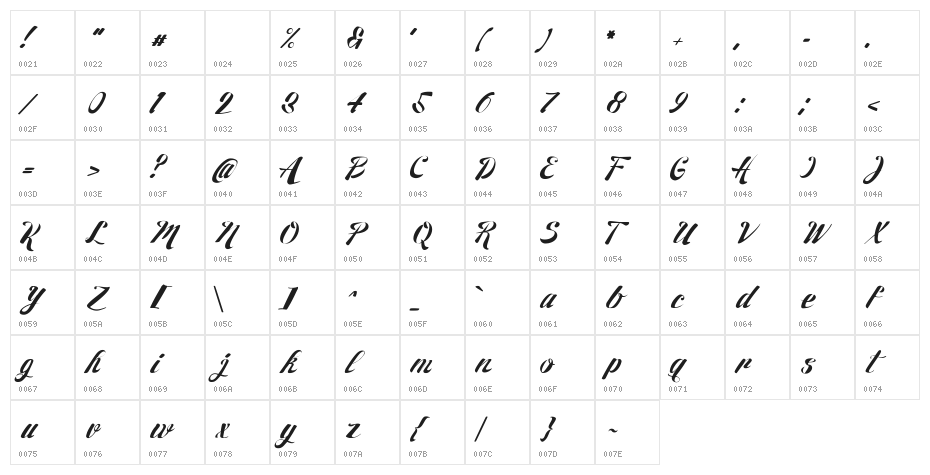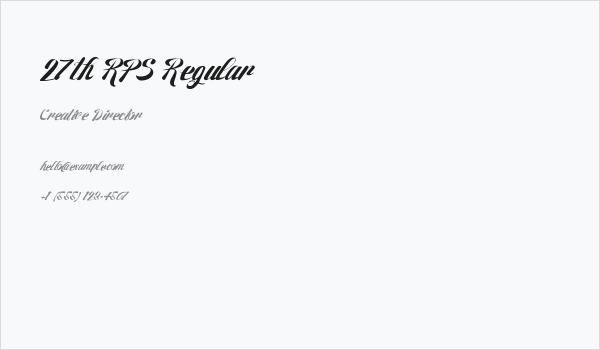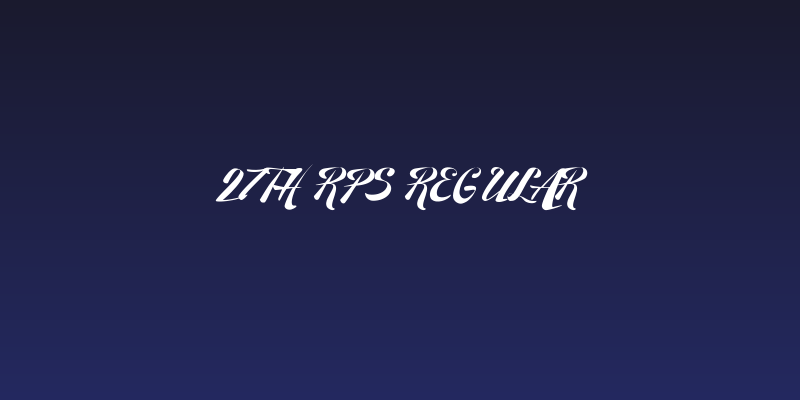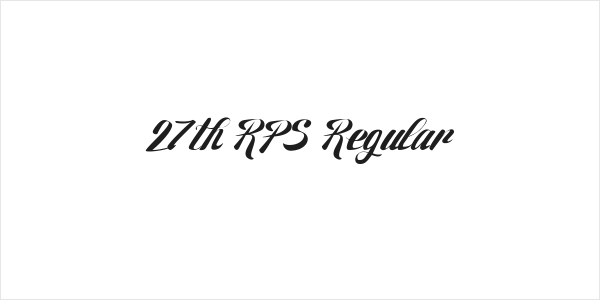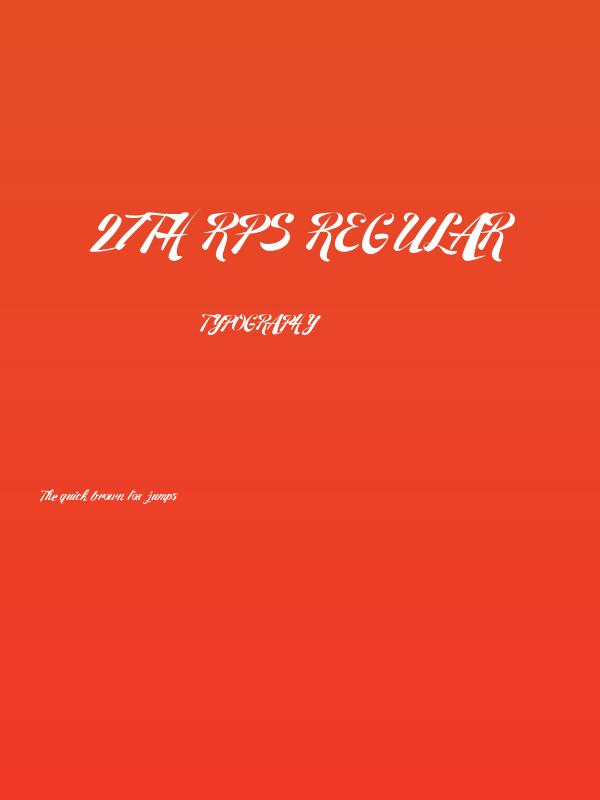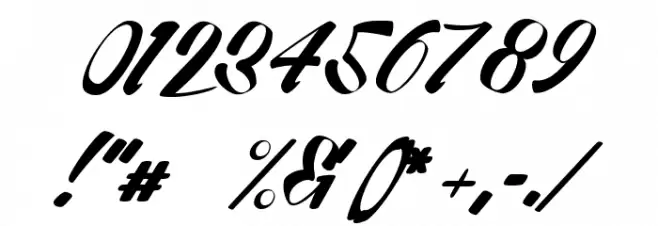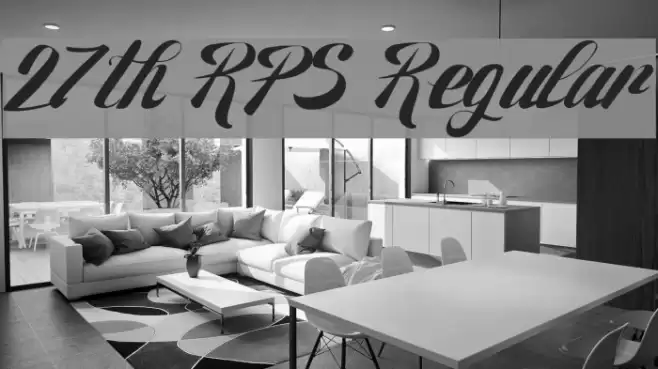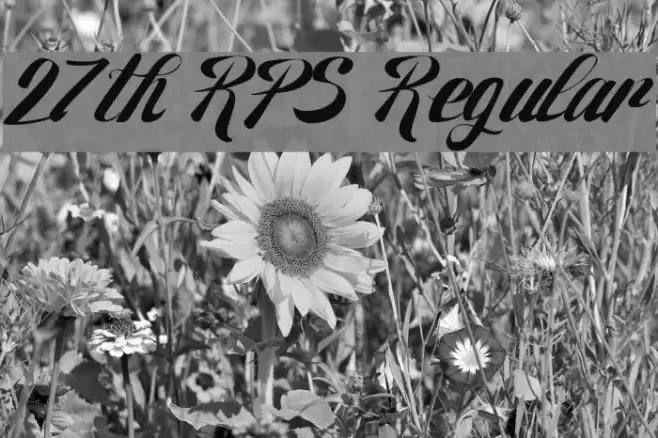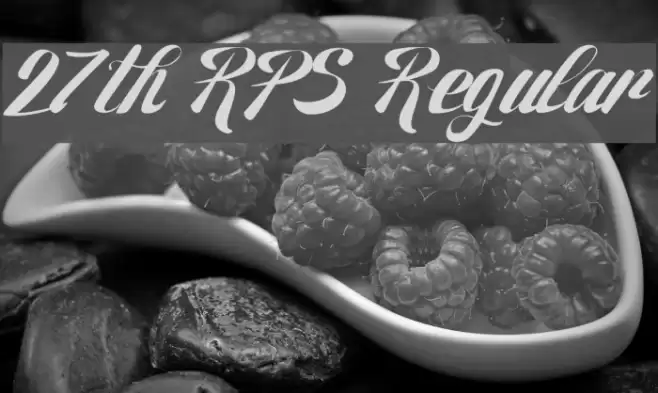
27th RPS Regular Font
| 全体的なスタイル | Elegant, Dynamic |
| 用途 | Logos, Invitations, Branding |
| おすすめプロジェクト | Ideal for wedding invitations, luxury branding, elegant packaging, and high-end product labels. |